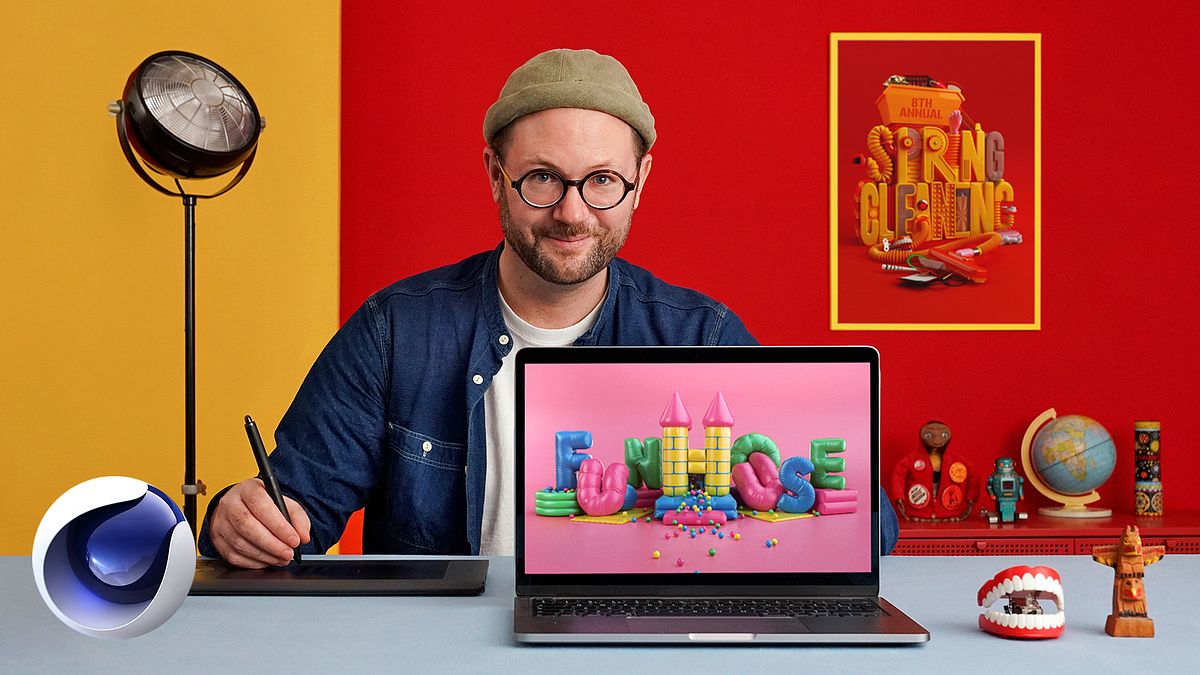
Typographie 3D : jouez avec la couleur et le volume
Thomas Burden est un illustrateur 3D de Chichester, au Royaume-Uni. Il est surtout connu pour son style visuel unique mêlant type 3D et engins, une esthétique influencée par les jouets qu'il n'a jamais été autorisé à avoir lorsqu'il était enfant.
• Les influences
Idées initiales et croquis
• Présentation du flux de travail logiciel
• Concepts initiaux et collecte d'inspiration
• Esquisser une disposition dans l'IA et exporter des chemins vectoriels
Tout sur Cinema 4D
• Configuration du document Cinema 4D
• Créer une esquisse 3D dans C4D
• Ajout de certains éclairages / textures de base et d'une caméra avec Redshift
• Modélisation des lettres 1
• Modélisation des lettres 2
• Modéliser le U
• Modélisation de la piscine à balles
• Modélisation des coussins
• Modélisation des tapis
• Modélisation du château 1
• Modélisation du château 2
• Modélisation du château 3
• Touches finales: ajout de la dynamique du tissu aux rideaux et de certaines balles à la scène 1
• Touches finales: ajout de la dynamique du tissu aux rideaux et de certaines balles à la scène 2
Touches finales à l'image finale
• Ajuster l'éclairage / affiner les paramètres de rendu
• Utilisation de Redshift AOV Manager
• Importation du rendu final et de l'AOV dans Photoshop: préparation des fichiers Photoshop pour l'édition
• Modification / affinage de l'image finale à l'aide des fichiers AOV
• Enregistrement de l'image finale en tant que fichier Photoshop Friendly Client
• Gonfler une lettre individuelle: pratique 1
• Gonfler une lettre individuelle: pratique 2
• Topographie 3D : jouez avec la couleur et le volume
Le cours vous apprend à collecter et analyser des références, en vous inspirant de jouets vintage, d'art populaire et de livres pour enfants pour créer des œuvres 3D uniques.
Oui, le cours aborde la simulation de tissus et la dynamique dans Cinema 4D pour obtenir des effets réalistes de gonflage et de corps souples dans vos modèles 3D.
Vous utiliserez à la fois le croquis numérique dans Illustrator et la modélisation 3D. Des bases en dessin sont utiles mais pas indispensables, car la majorité du travail est numérique.